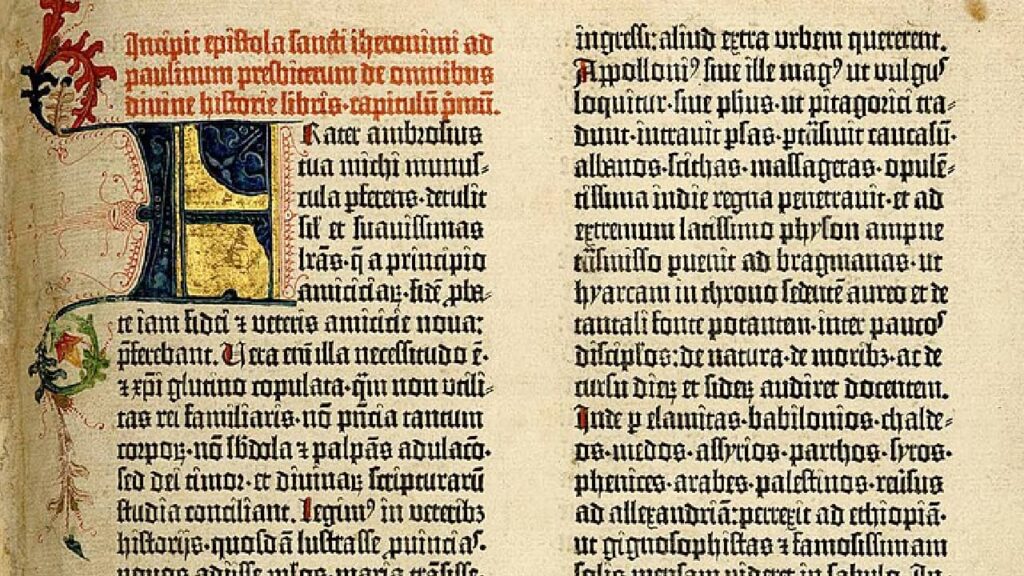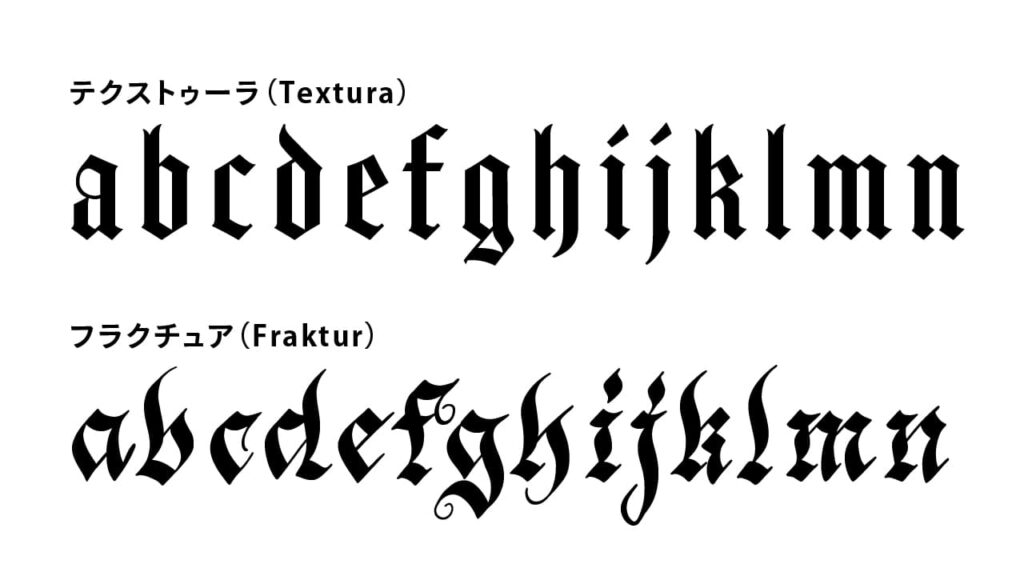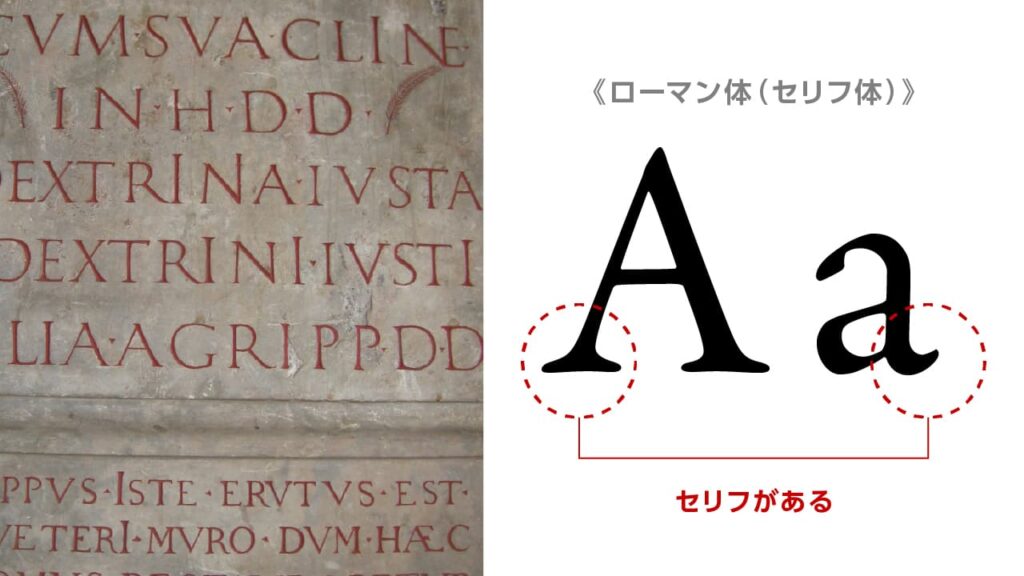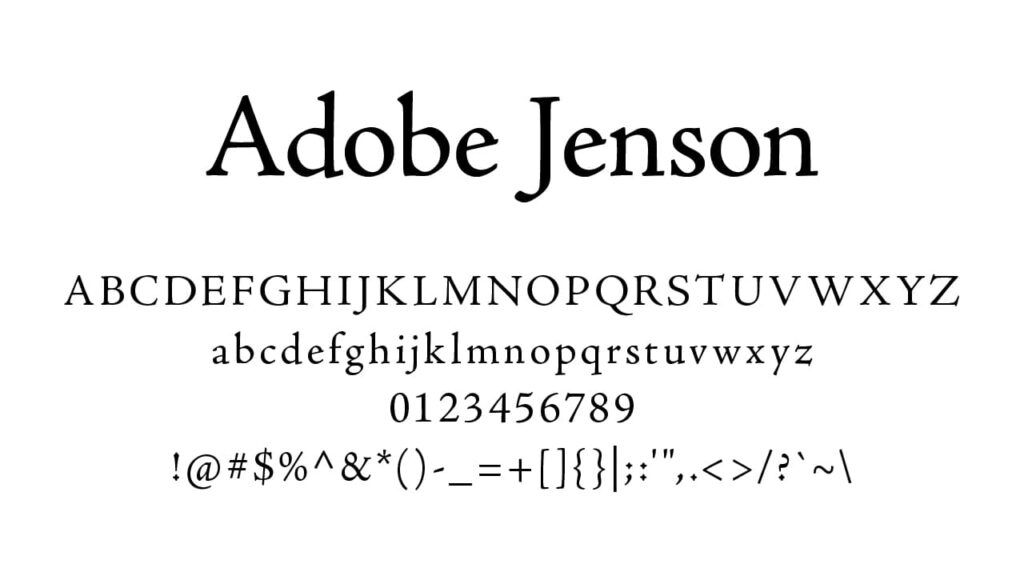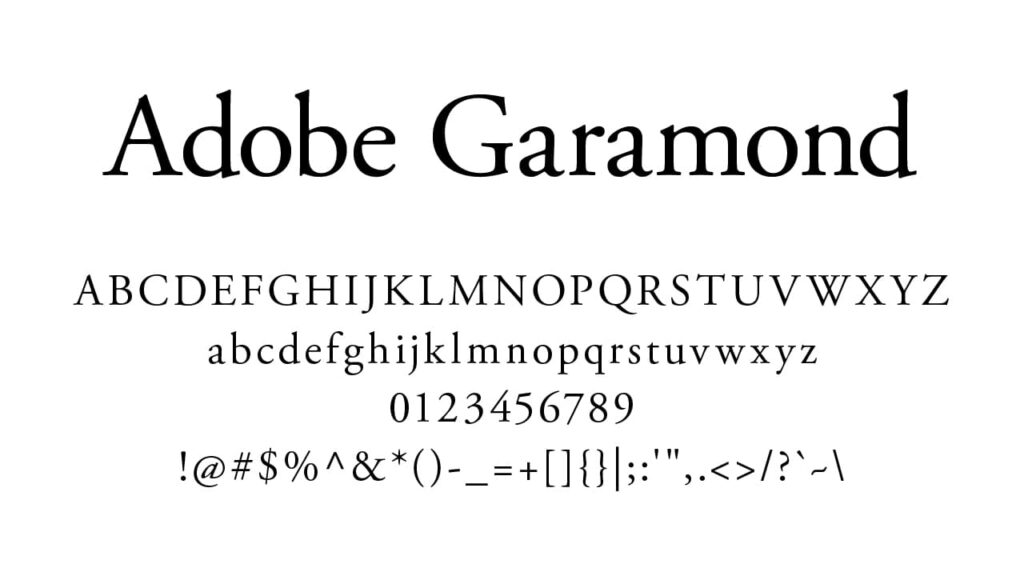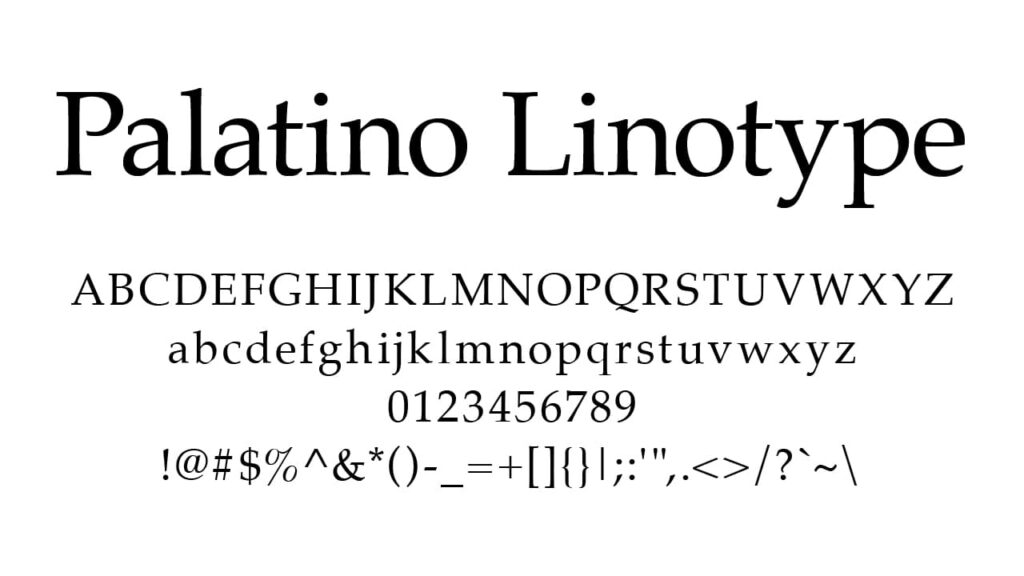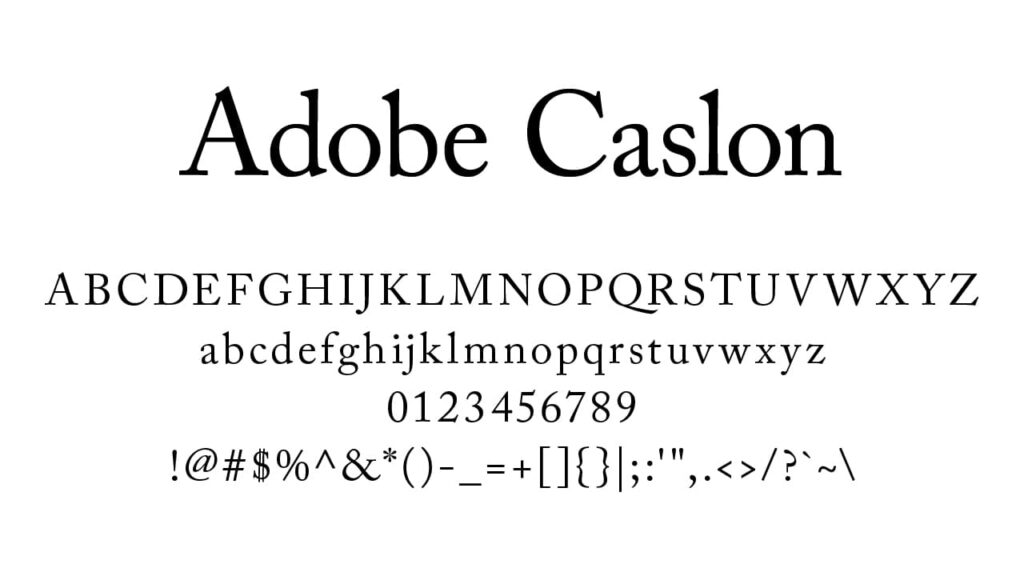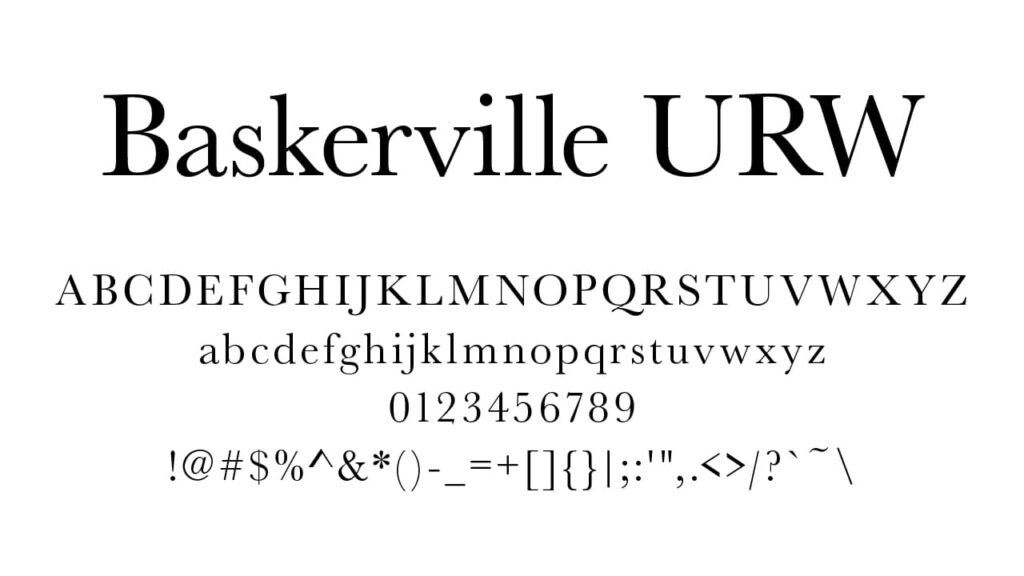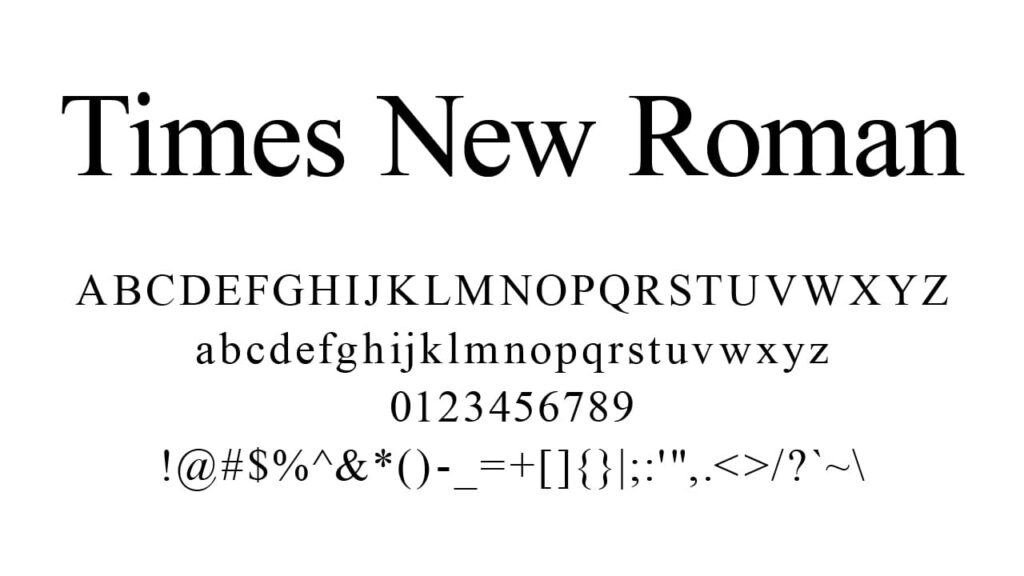
デザインに差がつく!書体の歴史を知ればフォント選びが変わる【欧文書体】
はじめに:文字のデザインが語るもの
フォント(書体)は単なる文字の形ではなく、文化や技術の歴史を映す鏡です。「フォントは言葉が身にまとう服」とも言われるように、文字のデザインひとつで伝わる印象や意味合いは大きく変わります。例えば、同じ言葉でも厳かなセリフ体で組めば伝統的でフォーマルな印象に、シンプルなサンセリフ体で組めばモダンで親しみやすい印象になるでしょう。フォントの歴史をひもとくことは、デザインの文脈を理解し効果的に使い分けるために重要です。
本記事では古代から現代までの欧文フォントの歴史を、時代ごとの代表的な書体と技術革新に沿ってわかりやすく解説します。ブラックレターからローマン体、スラブセリフ、サンセリフ、そしてデジタルフォントの登場まで、それぞれの時代背景と特徴、代表的な書体デザイナーや名作フォントを紹介します。また、Adobe FontsやGoogle Fontsで閲覧できる代表書体へのリンクも適宜掲載します。初心者の方にも理解しやすいよう専門用語も丁寧に説明し、フォントにまつわる豆知識や名言も交えながら、楽しく文字の旅へとご案内します。
ではさっそく、中世ヨーロッパの「黒い文字」の時代から始めましょう。
中世ヨーロッパ:ブラックレター体(黒文字)の時代
ブラックレター(Blackletter)は、中世ヨーロッパで広く使われたゴシック様式の筆記体・書体です。「黒文字」とも呼ばれ、平筆で書かれた文字の線が太く密集して紙面が黒く見えることに由来します。
12世紀頃に生まれたこの書体は、写本を手書きしていた修道士たちによって発展しました。やがて15世紀半ば、ドイツのヨハネス・グーテンベルクが活版印刷術を欧州にもたらし(1440年頃)、聖書の量産に成功した際にも、当時一般的だったブラックレター体を活字として採用しました。有名なグーテンベルク聖書(42行聖書)はまさにブラックレター活字で印刷されており、1日に3600ページもの大量印刷を可能にしたと伝えられます。
グーテンベルク聖書の1ページ(出典元:ウィキペディア)
ブラックレター体の特徴は、直線と曲線が複雑に組み合わさったとげとげしい字形と、文字同士が絡み合うような狭い字間です。代表的な形式にはテクストゥーラ(Textura)やフラクチュア(Fraktur)などがあり、特にフラクチュア体は16世紀以降ドイツで最も一般的な書体となりました。ドイツでは長らく公式文書や新聞にブラックレター体が使われ続け、第二次大戦中の1941年にナチス政権が「判読しづらい」という理由で使用禁止を布告するまで日常的に使われていたほどです。
ブラックレター体の代表として、グーテンベルクが聖書印刷に用いた活字(テクストゥーラ体に分類)や、その後ドイツで発展したフラクチュア体が挙げられます。
代表書体
Pirata One(ブラックレターの雰囲気を持つテクストゥーラ体フォント。Google Fonts: Pirata One)など。用途としては宗教書や荘重な印刷物に多く使われ、装飾的で重厚な印象から、現代でも新聞の題字やワインラベルなど伝統や格式を演出したい場面で見かけます。
豆知識: 活版印刷そのものは東洋でも独自に発明されていました。11世紀の中国・宋代に畢昇(Bi Sheng)が粘土による世界初の可動活字を作り、13世紀の高麗(朝鮮)では金属活字が登場しています。しかし欧文フォントの歴史は、グーテンベルクによる印刷革命を契機に本格的に展開しました。グーテンベルクの活版印刷は知の爆発的普及を促し、以後の書体デザインの進化の土台となったのです。
ルネサンス期:ローマン体(セリフ体)の誕生とオールドスタイル
15世紀後半、ルネサンスの人文主義者たちは中世のブラックレターに代わる読みやすい書体を求めました。彼らは「ブラックレターでは教会権威の香りが強すぎる」として敬遠し、代わりに古代ローマや古代ギリシアの文字に着想を得ます。こうしてローマン体(セリフ体)の原型が生まれました。
ローマン体とは、文字の端にセリフ(serif)と呼ばれる小さな飾り(ウロコ状の突起)を持つ書体で、古代ローマの碑文に見られる大文字が起源とされます。碑文を石に彫る際にできる彫り止まりの跡がセリフとなり、これが後の印刷用書体のデザインに受け継がれました。
なお、この古代ローマの碑文スタイルを現代に再現した代表的な書体が、Trajan(トレイジャン/トラジャン)です。1989年にキャロル・トウェンブリーによってデザインされたTrajanは、ローマ皇帝トラヤヌスの記念柱に刻まれた碑文に基づいており、現在でも映画のタイトルやブランドロゴに使われるなど、重厚で格式ある印象を与えるフォントとして愛用されています。
ヴェネチアン・ローマン(ベネチア風ローマン体)
最初期のローマン体は、15世紀後半のイタリア・ヴェネツィアで生まれました。ドイツ出身のスウェインハイムとパンナーツやフランス人ニコラ・ジェンソンらがヴェネツィアに印刷所を構え、人文主義者の手書き文字を元にした活字を作成したのです。1470年代にニコラ・ジェンソンが制作したローマン体は、ブラックレターよりも文字間隔が広く整然としており、格段に読みやすいものでした。これが「ヴェネチアン(ベネチア)ローマン体」と呼ばれる初期ローマン体です。代表例として、後世に復刻されたAdobe Jenson(アドビ・ジェンソン)などがあります。
オールド・ローマン(旧ローマン体)
ヴェネチアでローマン体が誕生してから数十年後、1500年前後にはアルドゥス・マヌティウスの工房でさらに改良されたローマン体が生み出されました。これが「オールド・ローマン」(オールドスタイルとも)と呼ばれる書体です。15世紀末~18世紀にかけてイタリアからフランス、オランダ、そしてイギリスへと伝わり各地で発展しました。フランスではルネサンス文化の隆盛の中で文字デザインも洗練され、パリの活字鋳造業者クロード・ガラモン(Claude Garamond)が1530年代に制作した書体は特に有名です。ガラモンのローマン体(ガラモン書体)はエレガントで可読性に優れ、後世「ガラモンド」として数多く復刻され愛用されています。実際、ガラモンド系のフォントは現在までに1000種類以上存在するといわれ、Apple社の有名な広告キャンペーンに使われたこともあります。代表書体は GaramondやPalatino(パラティーノ。20世紀にヘルマン・ツァップがデザインした旧ローマン体)など。
オールド・ローマン体はその後、オランダでは力強く無骨な「ダッチ・オールドスタイル」へ、イギリスではウィリアム・キャズロンによって優雅にまとめられたローマン体(Caslon)へと受け継がれました。18世紀前半のウィリアム・キャズロンの書体はイギリスで広く使われ、アメリカ独立宣言の印刷にも使われたと言われます。キャズロン書体は古き良き品格を備え、現代でも「信頼感」や「伝統」を演出したい場面で用いられる定番フォントです。
トランジショナル・ローマン(移行期ローマン体)
18世紀中頃になると、ローマン体はより近代的なスタイルへ移行し始めます。イギリスのジョン・バスカヴィルは、1750年代にそれまでのオールドスタイルの雰囲気を残しつつ、コントラストの強いシャープな書体を生み出しました。これが「トランジショナル(移行期)ローマン」に分類されます。バスカヴィルの書体はインクや紙の改良も相まって細部まで精緻に再現され、セリフ(ひげ飾り)はより細く鋭く、ストローク(筆跡の太さ)のコントラストは大きくなっています。このデザインは後に「モダンローマン体」へと発展する橋渡し的存在でした。代表書体はBaskerville(バスカヴィル)やTimes New Roman(タイムズ・ニューローマン、1932年にイギリス『タイムズ』紙のために制作された書体)など。Times New Romanはモダンとトランジショナルの中間的性格を持ち、新聞からパソコンまで幅広く使われる20世紀の代表格です。
18~19世紀:モダンローマン体と産業革命の書体
18世紀後半、産業革命期に入ると印刷技術や活字鋳造技術が飛躍的に向上し、書体デザインにも大きな変化が現れました。モダン・ローマン(Modern Roman)、いわゆるディド体・ボドニ体の登場です。モダンローマン体はトランジショナル体のすぐ後、フランスとイタリアで誕生しました。その特徴は、縦横のコントラストが極端に大きいこと。文字の縦画が非常に太く、横画や曲線が髪の毛のように細い(ヘアライン)ため、エレガントでモダンな印象を与えます。セリフも細く直線的になり、全体に垢抜けた繊細さが漂います。このデザインは当時最新の技術によって初めて実現可能となったもので、18世紀末に人々を驚かせました。
代表書体はフランスのフェルミン・ディドによるDidot(ディド)、イタリアのジャンバッティスタ・ボドニによるBodoni(ボドニ)が二大巨頭です。ディドとボドニはいずれも1790年前後に生み出され、その洗練された美しさからヨーロッパ中で高い評価を受けました。ディドは極限までコントラストを追求した女性的な優美さが特徴で、現代では『VOGUE』や『Harper’s BAZAAR』など高級ファッション誌のロゴに使われています。ただし細いヘアラインは小さい文字サイズでは潰れてしまうため、ディスプレイ用途(見出しやロゴ)に適しています。一方ボドニはディドよりややコントラストが穏やかで、セリフも控えめなため本文にも使用可能で上品な印象です。
モダンローマン体は19世紀に入るとイギリスでさらに発展し、ややコントラストを抑えた「スコッチ・ローマン」などの書体が生まれアメリカにも伝わりました。産業革命下の大量印刷時代に合わせ、読みやすさとエレガンスを両立したこれらのローマン体は、新聞・書籍から広告まで広く用いられるようになります。
スラブセリフ(エジプシャン)と広告の時代
19世紀、産業革命による市場拡大で広告やポスターが盛んになると、それまでの繊細な書体では視認性が足りなくなりました。そこで登場したのがスラブセリフ(Slab Serif)です。スラブセリフ体は文字のセリフが極端に太く角張った書体で、まるでサンセリフ体に厚みのある板状のセリフを付けたような力強いデザインが特徴です。ストロークの太さはほとんど変化がなく一定(モノライン)に近いため、遠目にもはっきりと認識できます。このスタイルはエジプシャンとも呼ばれ、ナポレオンのエジプト遠征(1798年)以降のエジプト熱にあやかって名付けられました。
世界初のスラブセリフ活字は1815年頃にイギリスのヴィンセント・フィギンズが発表したと言われます。また1817年にはウィリアム・キャズロン4世が「Italian」と呼ばれる奇抜な極太セリフ書体を発表し話題になりました(こちらは実用よりも奇をてらったものだったようです)。
アンティークプリント & ヴィンテージプリント、古い紙もの・古い洋書の専門店 Comfy design(コンフィーデザイン)
一般に広まったのは、ロンドンのロバート・ベズリーが1845年に発表したClarendon(クラレンドン)でしょう。クラレンドンは世界初の商標登録された書体とも言われ、太いセリフと安定感ある字形で見出しや広告に大ヒットしました。
Adobe Fonts/Clarendon URW
代表書体はRockwell(ロックウェル、幾何学的なスラブセリフの代表格。1934年モノタイプ社)、Courier(クーリエ、1950年代にタイプライター用にデザインされた等幅スラブセリフ体)など。現代ではウェブ用に最適化された Roboto Slab(Google Fonts: Roboto Slab)なども人気です。スラブセリフ体は視覚的インパクトが強く、19世紀当時は新聞の見出し・ポスター・商品のラベルなどに盛んに利用されました。現在でもヴィンテージ感や無骨な力強さを出したいデザインで活用されています。
Adobe Fonts/Rockwell
Adobe Fonts/Courier
Adobe Fonts/Roboto Slab
サンセリフ(Sans-serif)の誕生と普及
セリフ(飾り)のない書体、サンセリフ(Sans-serif、「サン=無い」+「セリフ」)の歴史も19世紀に始まります。
実はサンセリフ体自体は看板や碑文などでは古くから存在しましたが、印刷用書体として公式に現れたのは1816年、イギリスのウィリアム・キャズロン4世が活字見本帳に掲載したTwo Lines English Egyptianが最初と言われます。これは大文字のみの書体で商業的にはあまり注目されませんでしたが、サンセリフ活字の出発点となりました。その後1830~40年代にかけて、見出し用の太く装飾的なサンセリフ活字(当時は「グロテスク」や「ゴシック」と呼ばれた)が登場し、徐々に利用が広がっていきます。
引用元:Caslon Egyptian(Wikipedia)
本格的にサンセリフ体が脚光を浴びるのは19世紀末から20世紀初頭です。1898年、ドイツで発売されたAkzidenz-Grotesk(アクチデンツ・グロテスク)は、ヘルベチカの前身とも言えるシンプルなサンセリフ書体で、欧米のデザイナーに衝撃を与えました。
Adobe Fonts/Akzidenz-Grotesk Next
20世紀に入るとモダニズムの潮流とともに「装飾を排した機能美」としてサンセリフがもてはやされ、多くの名作が生まれます。例えば、幾何学的な基本形からなるドイツのFutura(フツラ、1927年、パウル・レナー作)や、人間の筆跡に近いプロポーションを持つ英国のGill Sans(ギル・サン、1928年、エリック・ギル作)が登場しました。戦後にはスイスでHelvetica(ヘルベチカ、1957年、マックス・ミーディンガー作)とUnivers(ユニバース、1957年、エイドリアン・フルティガー作)が発表され、どちらも洗練された汎用サンセリフとして世界的に大ヒットします。特にHelveticaは「世界で最も愛されるフォント」と称されるほど看板・企業ロゴ・公共サインなど至る所に使われています。まさに「現代の空気」のような存在です。
Adobe Fonts/Futura PT
Adobe Fonts/Gill Sans Nova
Adobe Fonts/Helvetica
Adobe Fonts/Univers Next
豆知識: Helveticaという名前はラテン語で「スイスの」という意味(Helvetia=スイスのラテン名)で、スイス生まれの書体であることに由来します。一方、同じく有名なサンセリフArialは、Helveticaの影響を受けて1982年に制作された類似書体です。Windowsなどに標準搭載され普及しましたが、デザイナーの間では「Helveticaの代替品」とみなされることも多く、Helveticaほどの評価は得られていません。
20~21世紀:写真植字からデジタルフォントへ
写真植字と電子組版への転換
1900年代中盤、活字による組版は写真植字(フォトタイプセット)技術へと置き換わっていきます。写真植字機ではフィルム上の文字を拡大投影して版下を作るため、金属活字の制約から解放されました。これにより書体デザインはより自由になり、極端に太い・細いウェイトや斜め角度のバリエーションなど、多彩なフォントが作られるようになります。ただし写真植字時代のフォントは物理的な文字盤やフィルムが必要で、高価で専門的なものでした。
文字盤と写植機/引用元:株式会社写研(https://archive.sha-ken.co.jp/
転機は1980年代、個人向けコンピュータとレーザープリンタの登場です。1984年、Apple社のMacintosh(マッキントッシュ)が発売され、画面上で様々な書体を扱える初のパソコンとして注目を集めました。当時Appleの創業者スティーブ・ジョブズは大学でカリグラフィー(書道)の授業に影響を受けており、「Macに美しいフォントを搭載することは最重要事項の一つだった」と語っています。ジョブズのこだわりにより、Macintoshには複数のプロポーショナルフォント(文字幅が文字ごとに異なる書体)が搭載され、誰でもコンピュータ上で字体を選べる時代が始まりました。これは文字デザインの民主化への大きな一歩でした。
初代マッキントッシュ「マッキントッシュ 128K」
1985年には「デスクトップパブリッシング(DTP)」革命が起こります。AppleのLaserWriterというレーザープリンタと、Aldus社のPageMakerという画面組版ソフトが登場し、個人でも紙面レイアウトと印刷が完結できるようになったのです。従来は専門の写植オペレーターに依頼していた印刷物の版下作りが、デザイナー自身の手でPC上で行えるようになり、出版・デザイン業界に大きな変革をもたらしました。Adobe社が開発したPostScriptフォント技術や、後にAppleとMicrosoftが共同開発したTrueTypeフォント(1991年)など、デジタルフォントの規格も相次いで策定され、数多くの書体がデジタルデータ化されました。
1990年代にはDTPの普及とともに、HelveticaやTimesなど古典的な書体から、新しくデザインされた書体まで、数えきれないフォントがPCで使えるようになります。特に1990年代後半にかけてはWindowsやMacに標準で数十書体が搭載され、ArialTimes New RomanCourier NewGeorgiaといった汎用フォントが世界中で共有される「標準フォント時代」でもありました。
Webフォントと可変フォント:新たな展開
インターネットの登場はフォントの世界にも新たな章をもたらしました。初期のウェブでは、閲覧者のPCにインストールされた一部の「ウェブセーフフォント」(例えばArialやTimes等)しか使えず、デザインの幅が限られていました。しかし2010年頃、Web Open Font Format(WOFF)の勧告制定やGoogle Fontsのサービス開始などにより、ウェブページに任意のフォントを埋め込んで表示できる「Webフォント」が急速に普及しました。今では数百種以上のフォントがウェブ上で無料利用でき、ブランドサイトやブログでも印象に合った書体を自由に使えます。例えば本記事でリンクしているようなAdobe FontsやGoogle Fontsは、その代表的なオンラインフォントライブラリです。
直近の大きな革新としては可変フォント(Variable Font)技術の登場があります。可変フォントは1つのフォントファイル内に太さ・幅・傾きなど複数のスタイルを埋め込み、自由に連続的な調整ができる技術です。2016年9月、Adobe・Apple・Google・Microsoftの連名でOpenTypeフォント仕様の拡張として発表されました。例えば従来は「Light」「Regular」「Bold」など別々のファイルだったものが、可変フォントでは一本のファイルで無段階のウエイトを実現できます。これによりウェブサイトのパフォーマンス向上やデザインの柔軟性向上が期待され、近年対応ソフトや対応フォントが増えています。
21世紀の今、フォントデザインはかつてないほど多様化・大衆化しています。プロのタイポグラファーによる高品質な商用フォントから、コミュニティ発のオープンソースフォント、さらには企業が独自開発するカスタムフォントまで、実に膨大な選択肢があります。コンピュータの画面解像度向上や印刷技術の進歩で、美しいタイポグラフィを再現する環境も整いました。フォントはもはや専門家だけの道具ではなく、学生や若手デザイナーでも自由に使いこなせる表現手段となっているのです。
おわりに:歴史を知りデザインに活かす
長い旅路を経て進化してきたフォントの歴史を振り返ってきました。中世のブラックレターからルネサンスのローマン体、産業革命のスラブセリフやサンセリフ、そしてデジタル時代の多彩なフォント群まで、それぞれの書体には生まれた理由と背景があります。その時代ごとの制約や目的が書体デザインに反映されているのです。
デザイナーにとってフォント選びは、単に見た目の好みだけでなくメッセージをどう伝えるかという本質に関わります。歴史を踏まえて書体を選定すれば、「なぜこのフォントなのか」に筋が通り、デザインに説得力が生まれます。例えば、クラシックな雰囲気を求めるならガラモンなどのオールドスタイル、モダンで高級感を出すならディド体、力強いインパクトが必要ならスラブセリフやサンセリフの太字、といった具合です。それぞれの書体が持つ“声”を理解し使い分けることで、読み手の心に響くデザインが可能になるでしょう。
最後にもう一度、冒頭の言葉を振り返ります。「フォントは言葉が身にまとう服」。文字という内容に対し、フォントという視覚的な装いを与えることで、私たちは文章の印象を自在にコントロールできます。ぜひ歴史で学んだ知識を活かして、あなたのデザインに最適な“言葉の服”を選んでみてください。タイポグラフィの奥深い世界は、学べば学ぶほど面白く、きっとデザイン表現の力強い味方になってくれるはずです。